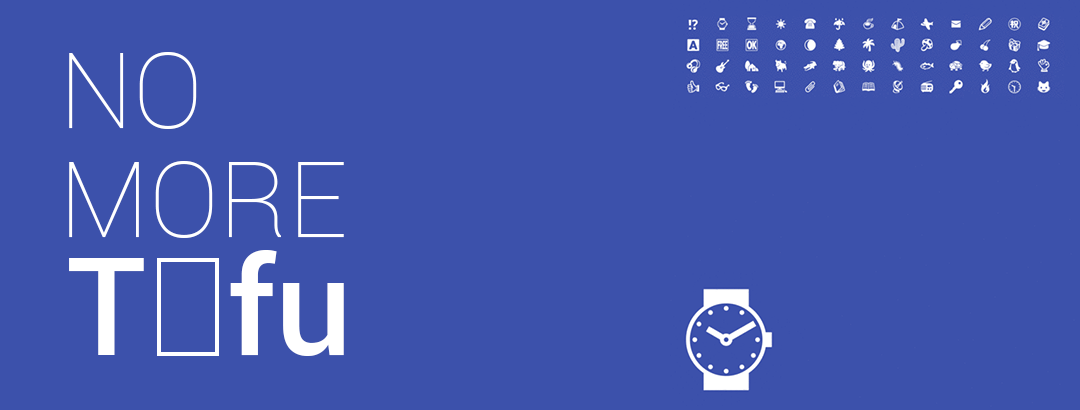
Google anunció hace unos meses uno de los mayores proyectos de tipografía. Noto es una familia de fuentes tipográficas que cubre más de 800 lenguas diferentes.
El proyecto de colaboración entre Google y monotype que ha durado mas cinco años y es uno de los mayores proyectos de tipografía de los últimos tiempos. Y como no podía ser de otra forma tal y como nos tiene acostumbrados Google, es de código abierto y gratis para descargar.